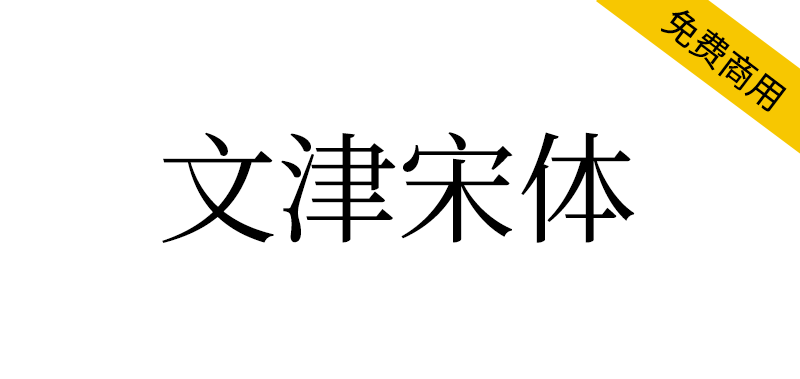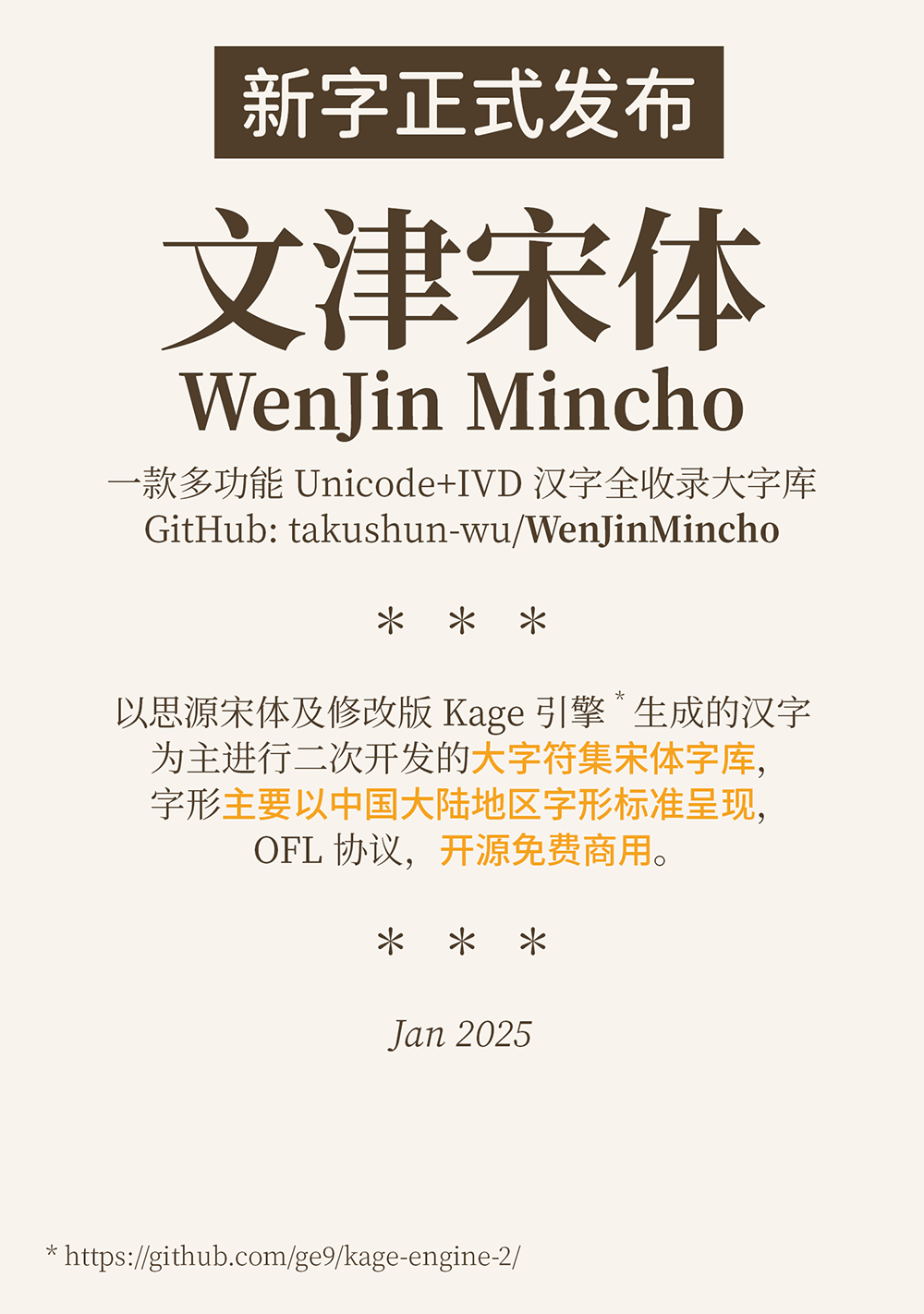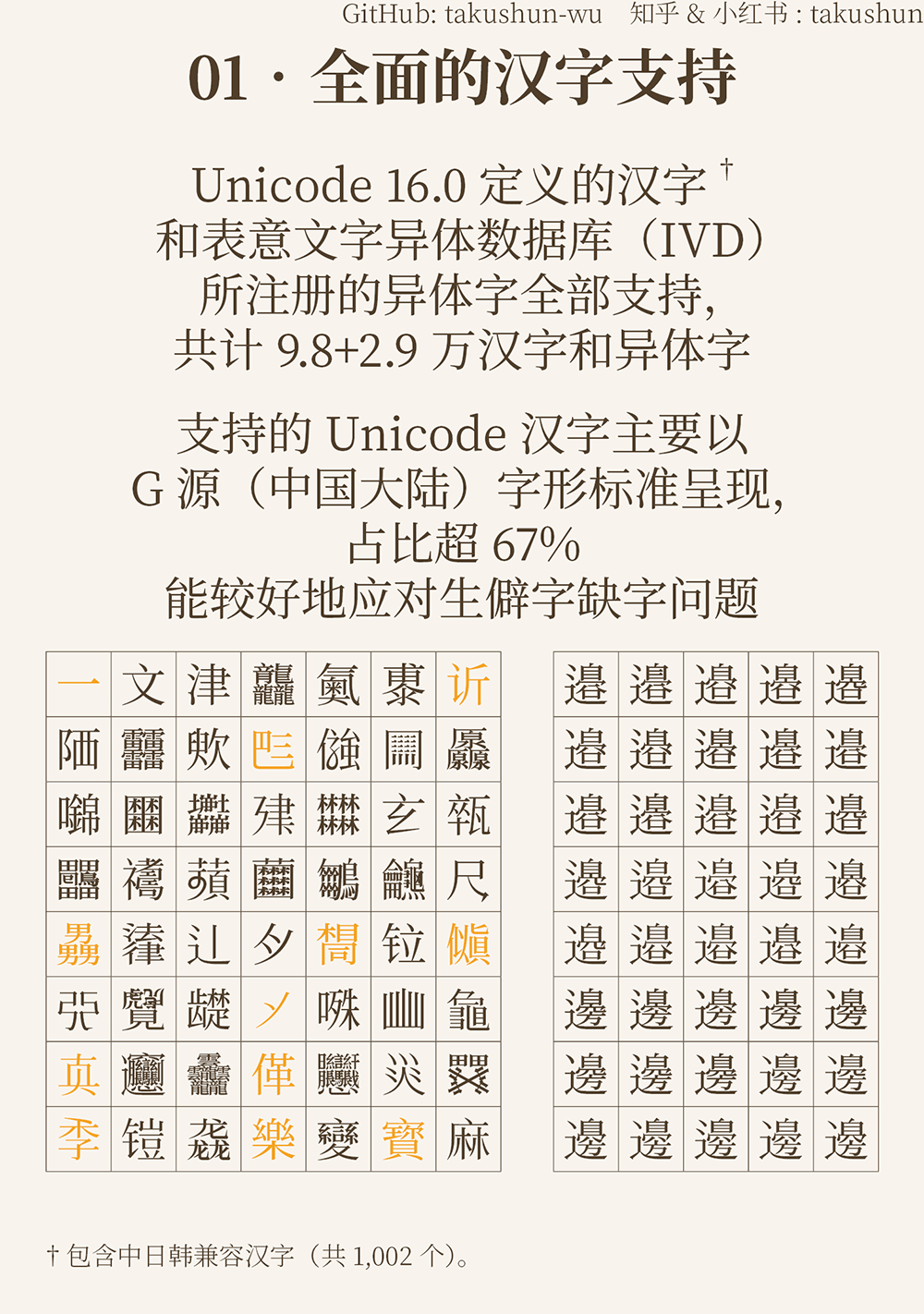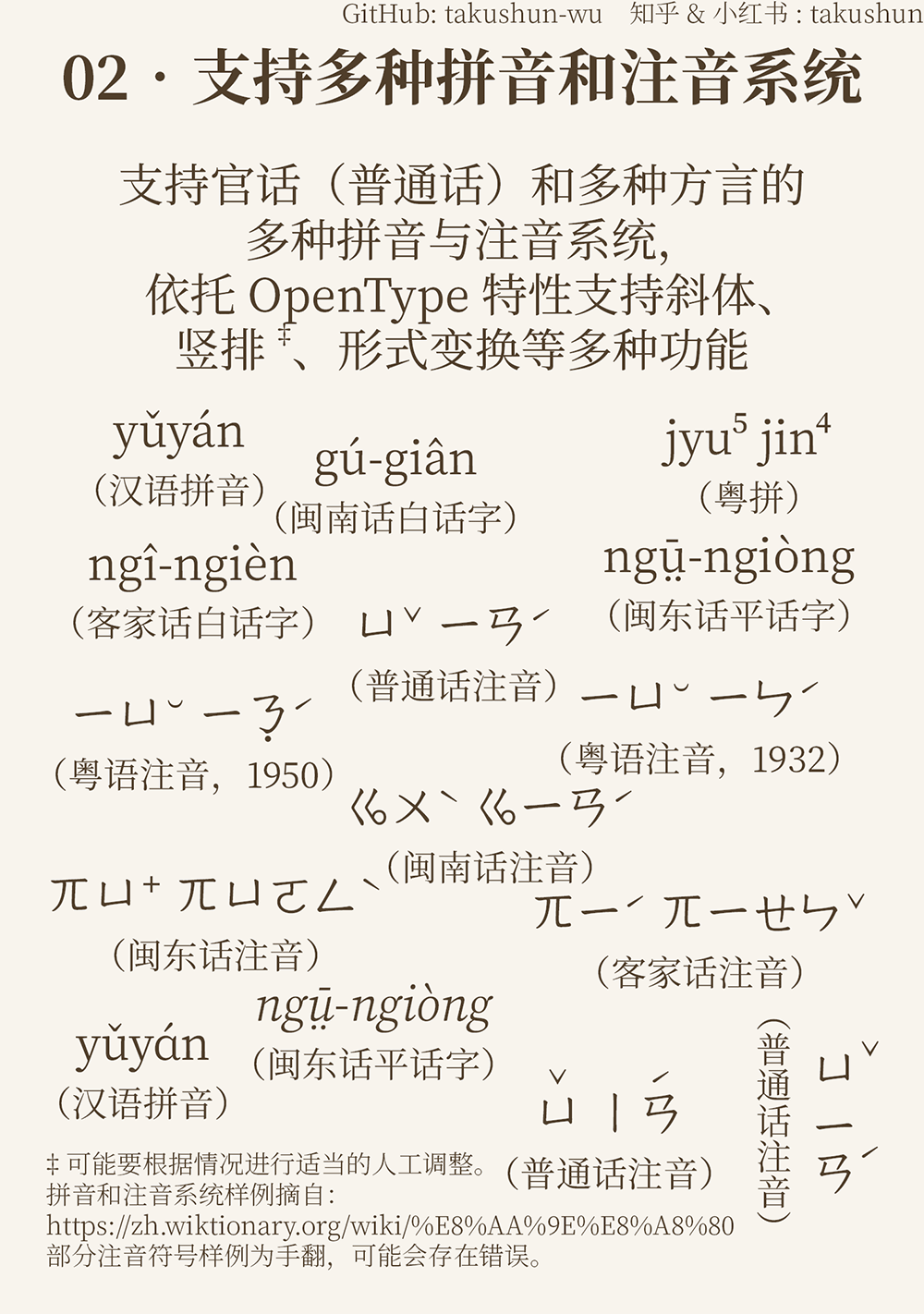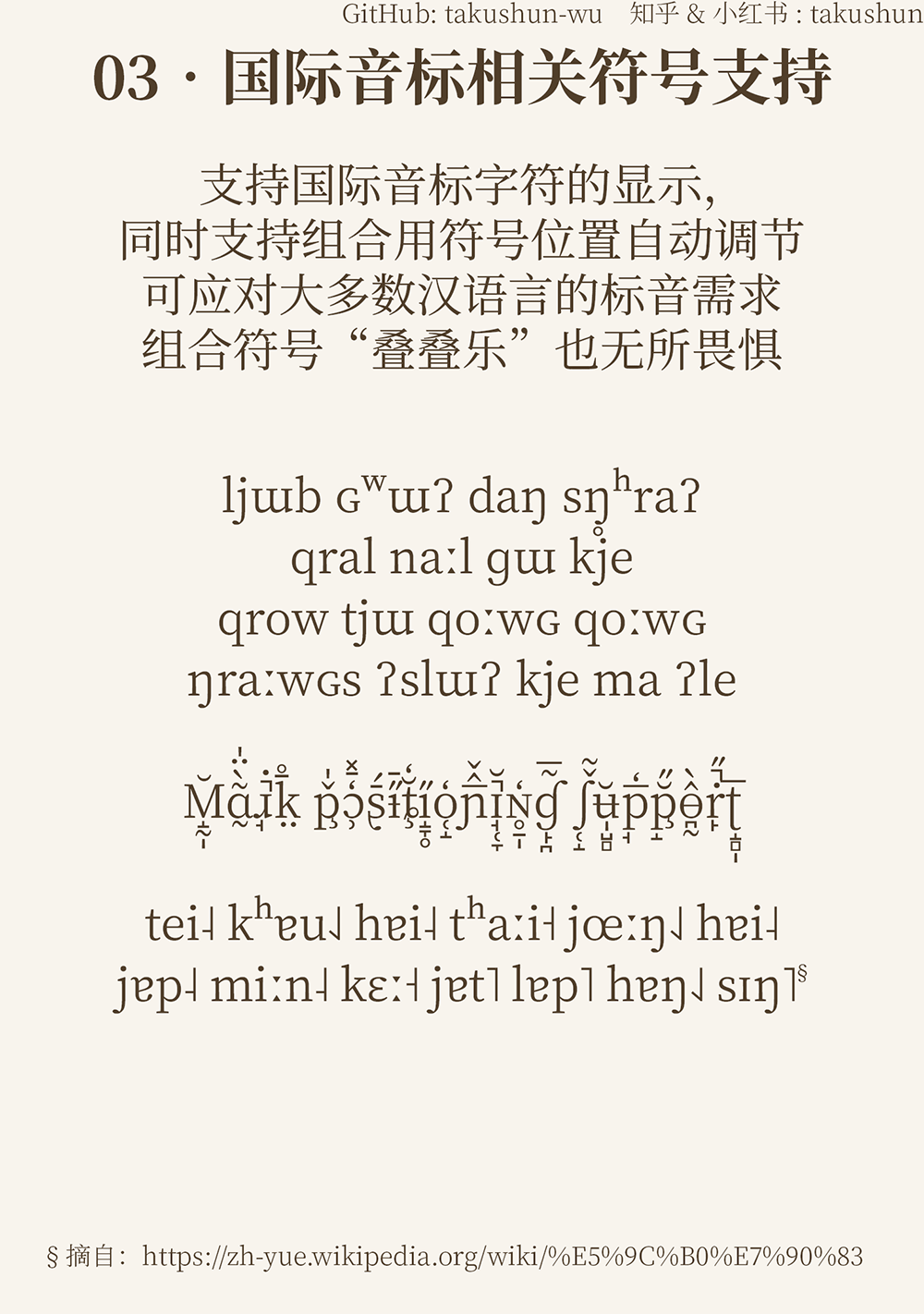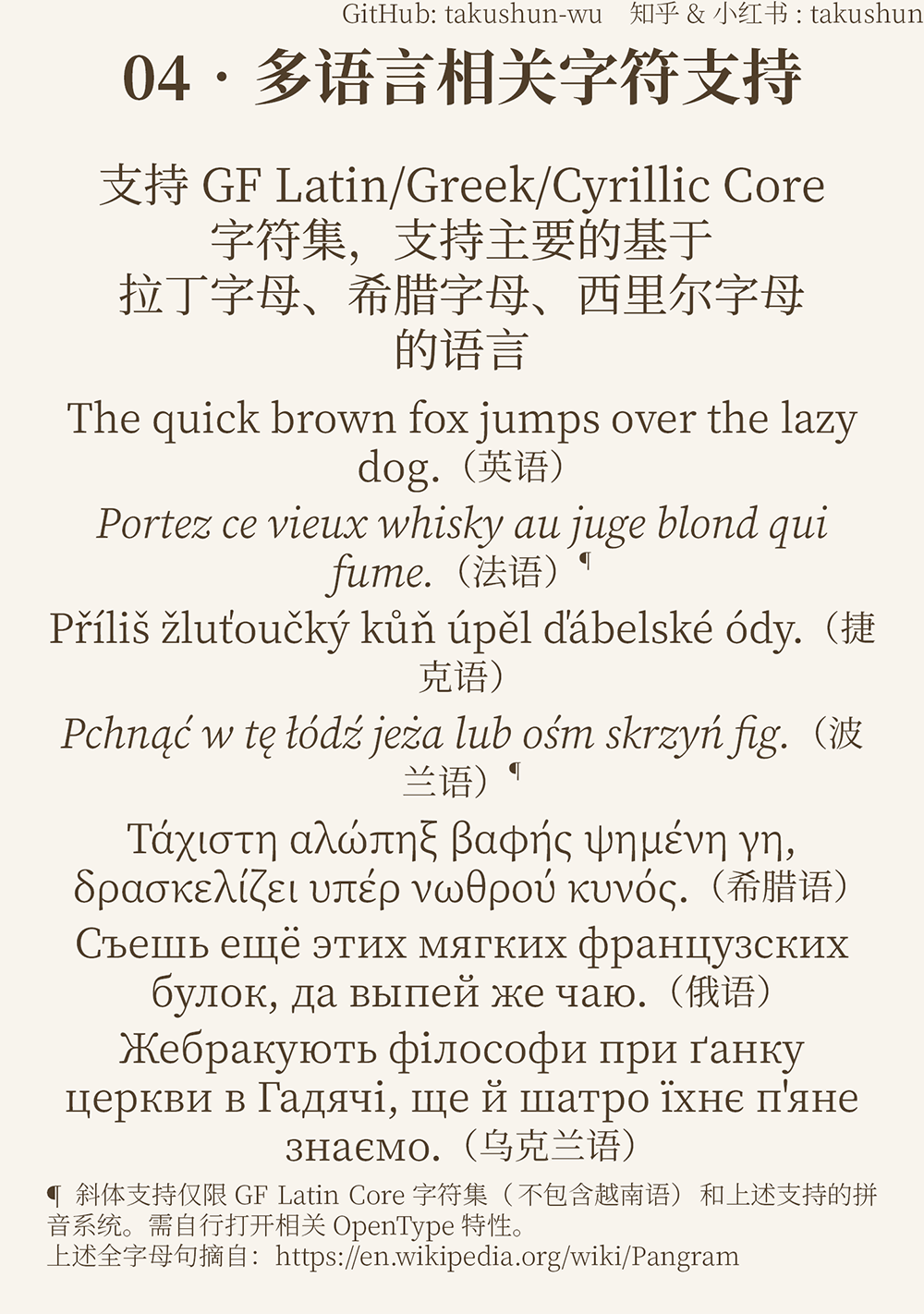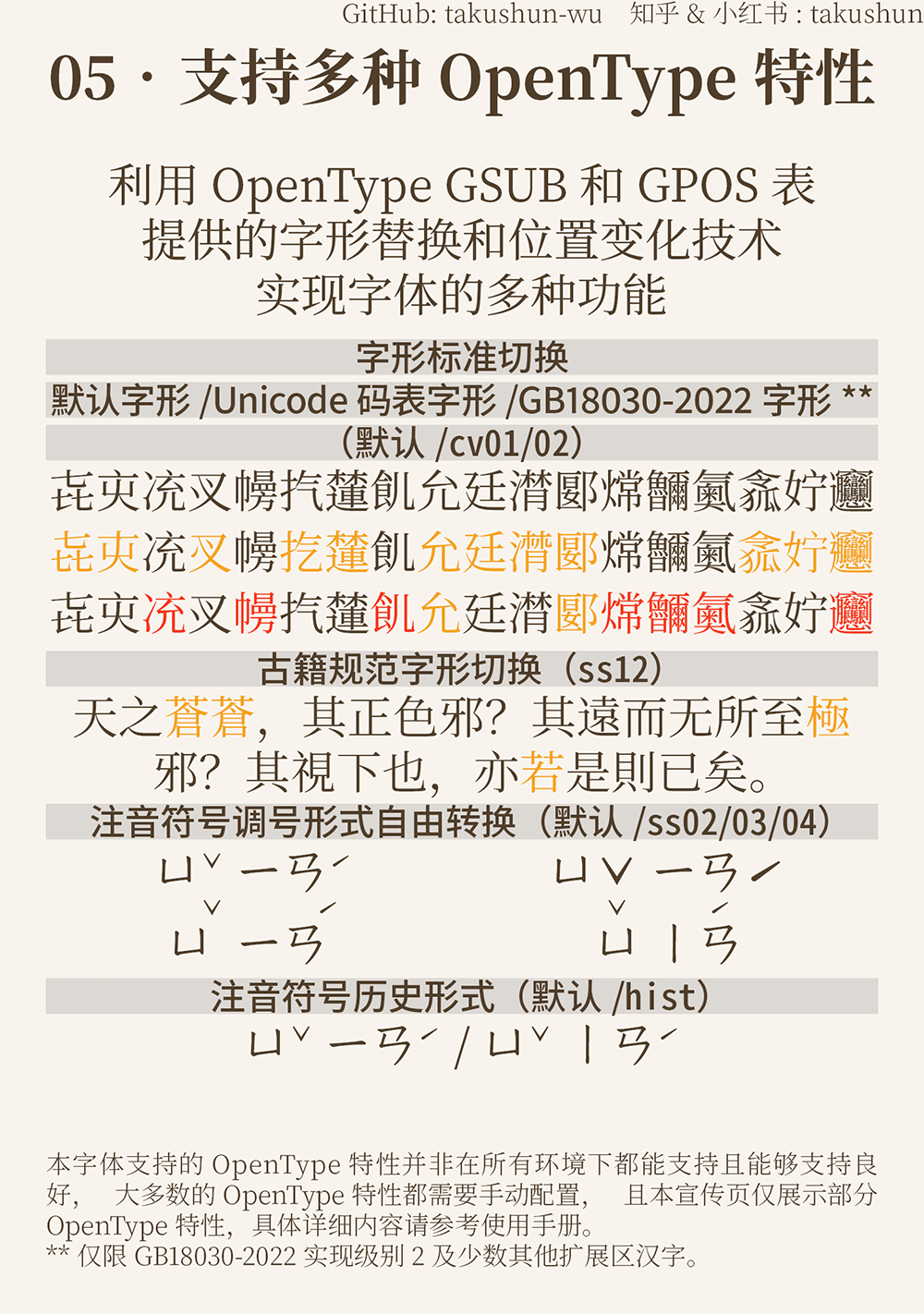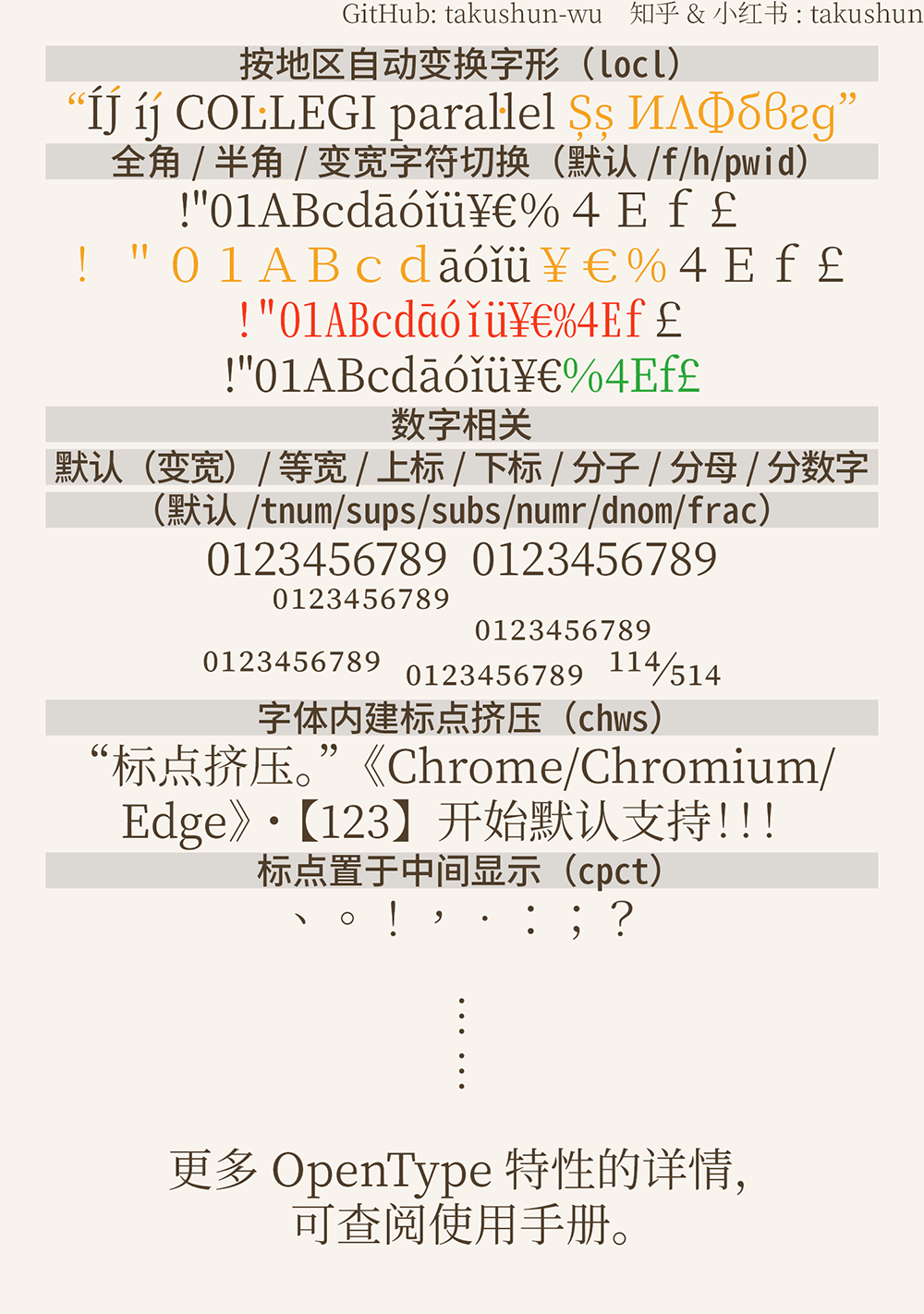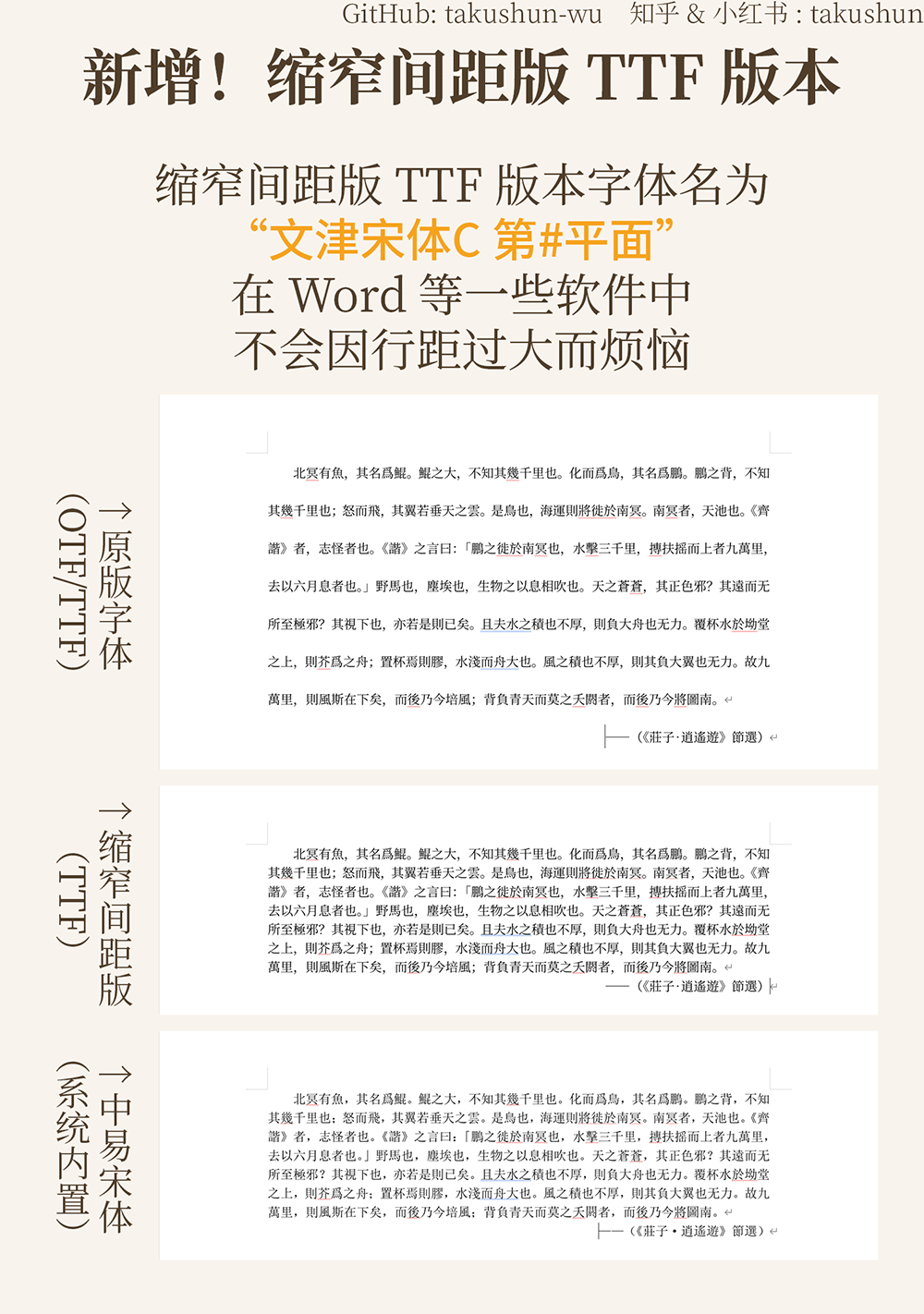
文津宋体是一套以思源宋体及其衍生版本、利用GlyphWiki数据和修改版Kage引擎生成的汉字为主进行二次开发的大字符集宋体字库,实现Unicode定义的汉字和表意文字异体数据库(IVD)注册的字形全覆盖,其中Unicode汉字字形主要以中国大陆地区字形标准呈现。该字体系列采用OFL协议,任何个人与团体均可免费商用。
除此之外,文津宋体还支持多种拼音和注音系统,并配备了多种OpenType特性可供自由调用,主要包括字形标准切换、拼音/注音变种符号支持、注音符号竖排支持、带标字符的正确定位、标点挤压等。